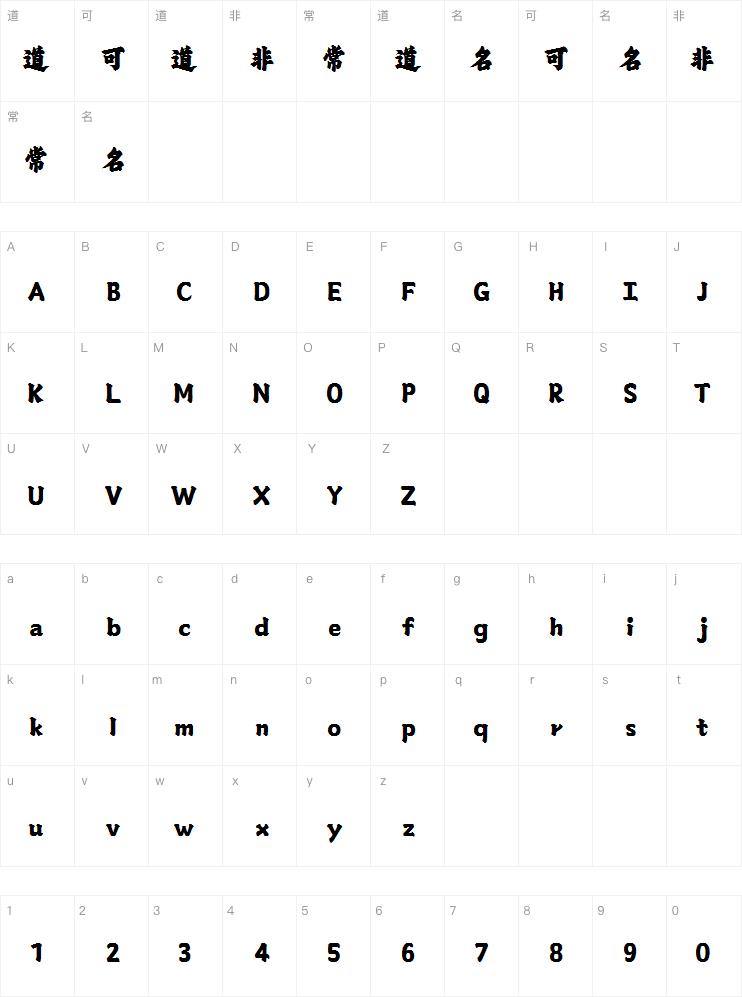
山海盛唐榜书,是一款全新的字体,包含简繁汉字9169个,符号200+个,是一款大字榜书字体。该字体雄健有力,非常醒目!有力、宽厚,如同巍峨的大山,充满了稳重感和设计感。古朴浑厚,笔画与字形间透露着榜书的古雅和刚劲的特点,在浑厚的同时而又极富张力,桀骜不驯的特性,霸气外露。该字体汲取中国唐代书法家颜真卿书法的颜体之特性和柳宗元书法的柳体之特性,在汲取中创新,结合当代设计视觉环境,融入现代审美。它的笔画充满力量感,组合搭配极富强烈的节奏感。在粗细的纵横间,拥有非常规的张力特性。从而使得该字体字形在浑厚的同时而又极富张力。它的笔画充满力量感的同时,又蕴含着朴拙感。在粗细的纵横间,拥有非常规的张力特性。笔画的楷书运笔笔势效果使字体的气息更加流畅,笔画间的关系密不可分,同时也增加了字体的自由洒脱之感。这款字体古韵悠扬而不失灵动,静中有动,收放有序,适合作为标题字体应用于书籍封面、影视标题、展览广告等多种